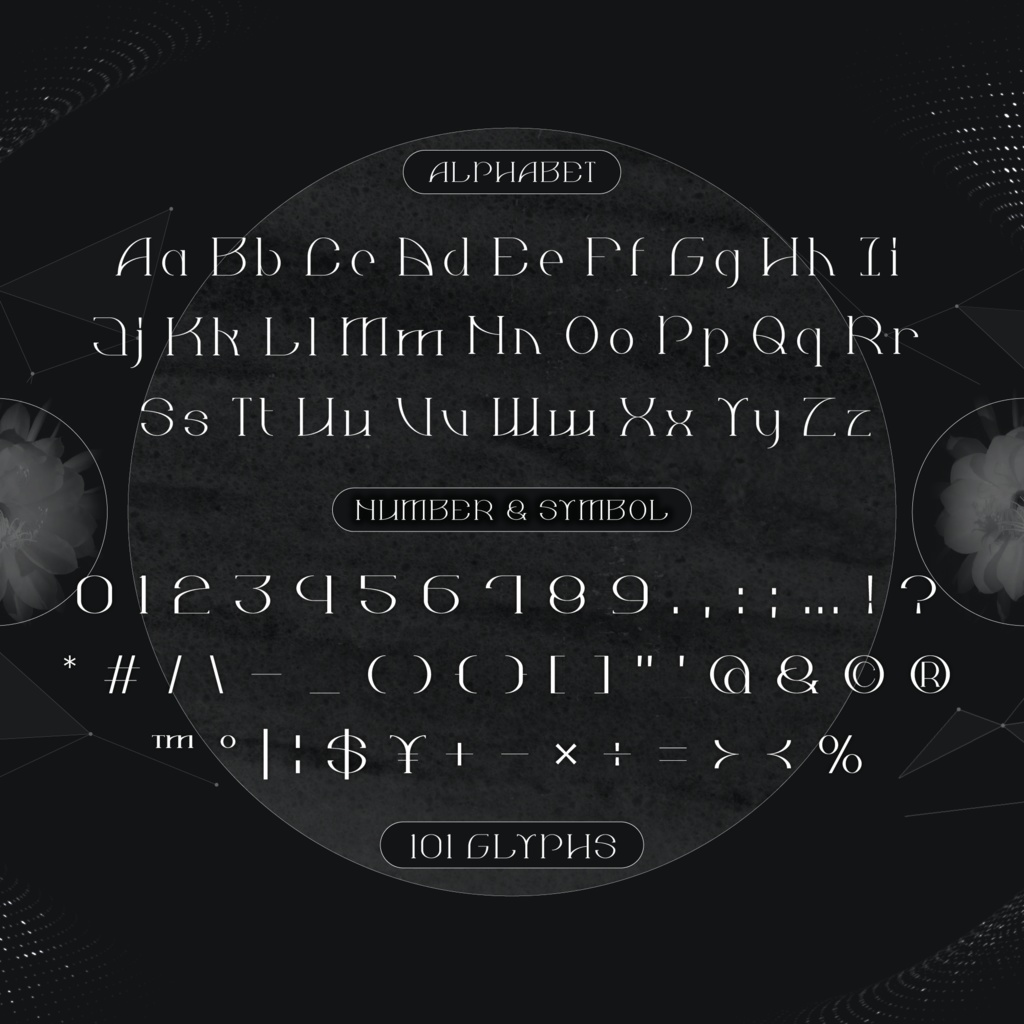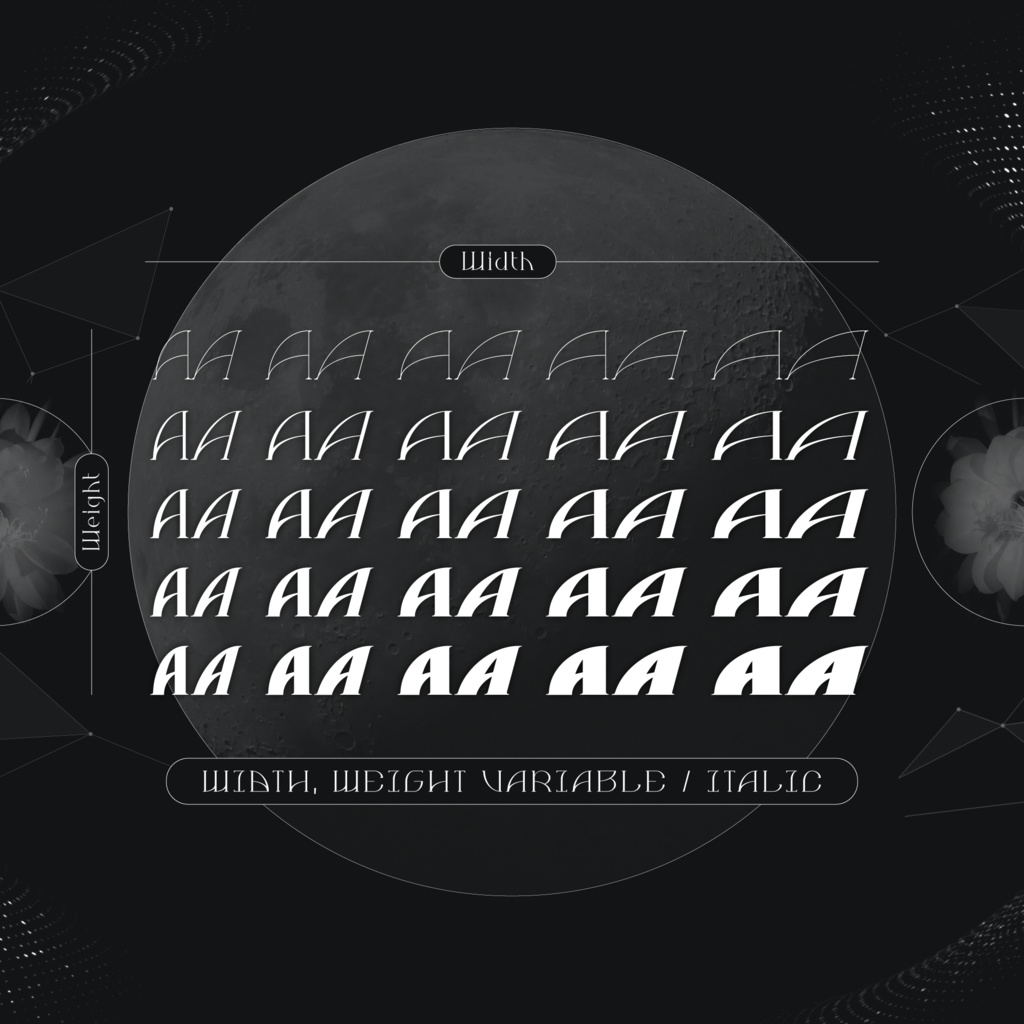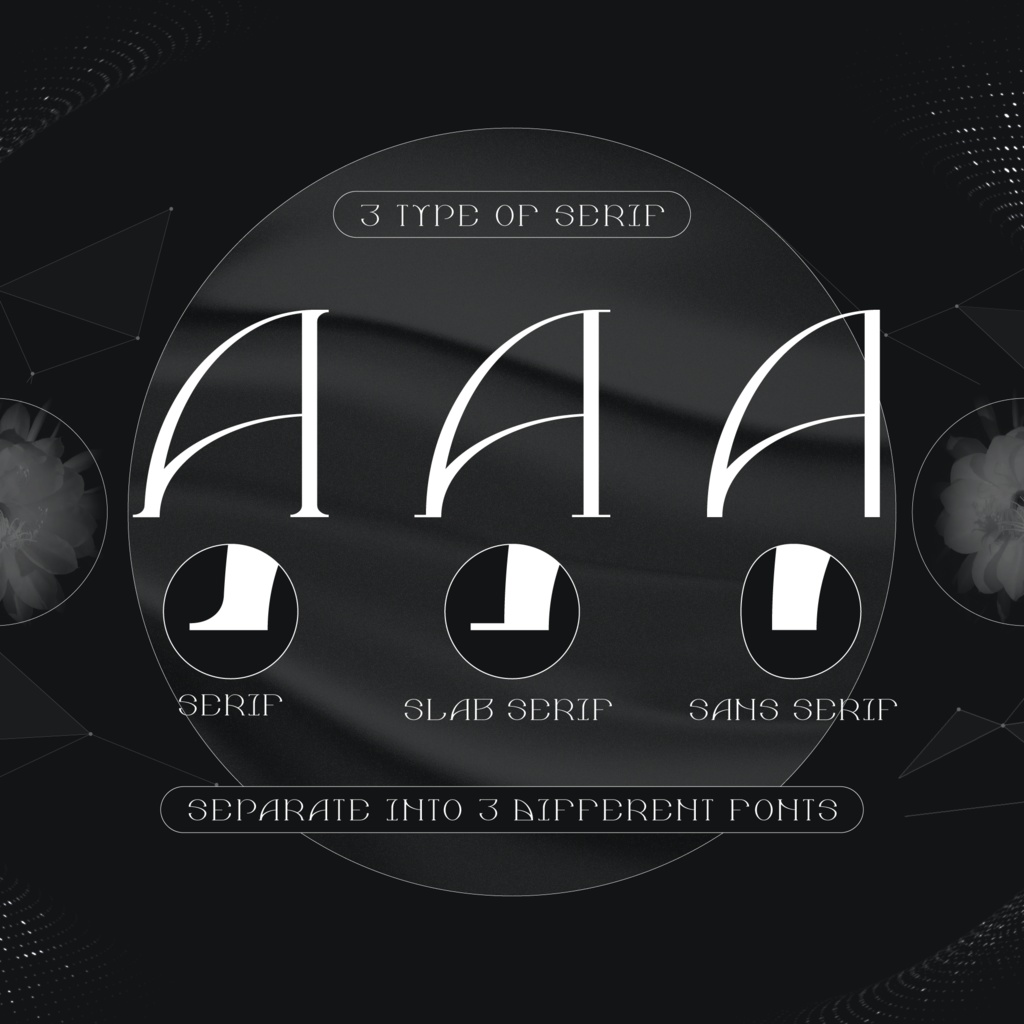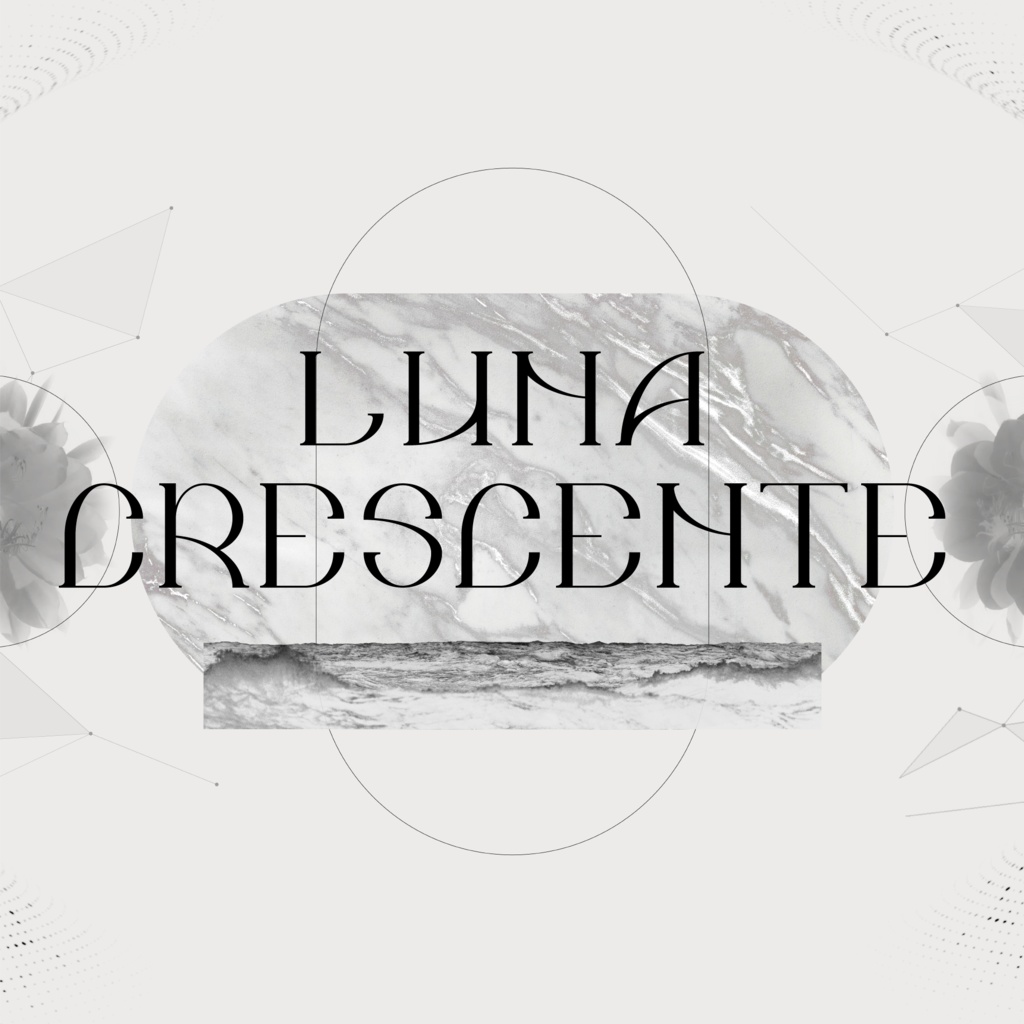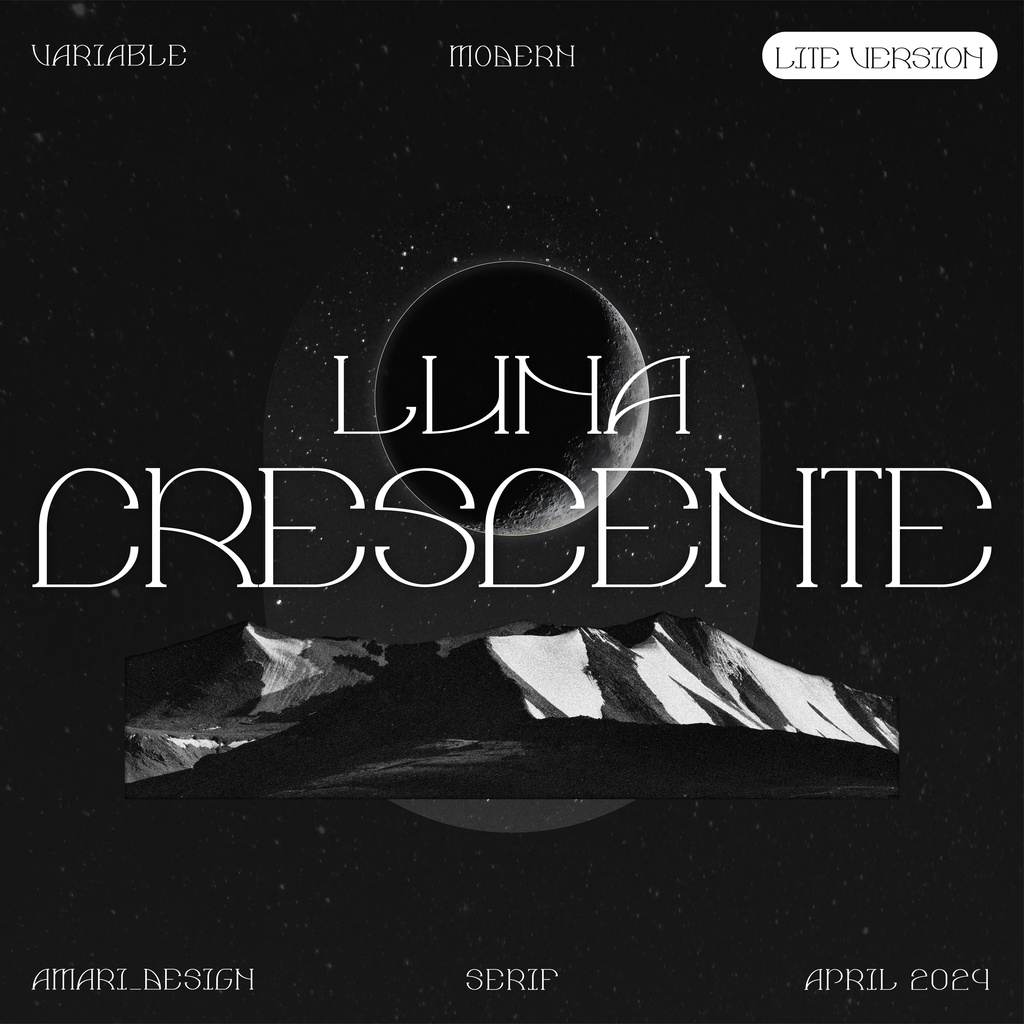
【可変セリフフォント】Luna Crescente / 上弦の月 - 0.95
月相からインスピレーションを得た、古典的なセリフフォントです。細い線で軽快な印象を与え、可変幅調整機能により、より広い空間感を表現できます。 レトロな芸術作品や未来風も最適で、遠目には神秘的で魅力的な雰囲気、近目には統一感と読みやすさがあります。
ラテン文字、句読点と数学記号合計で102グリフが含まれています。 字幅、太さ可変。斜体も対応,3つセリフ選択肢のフォント。